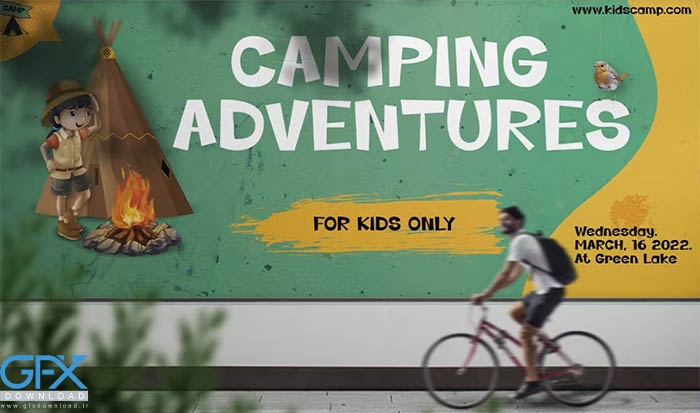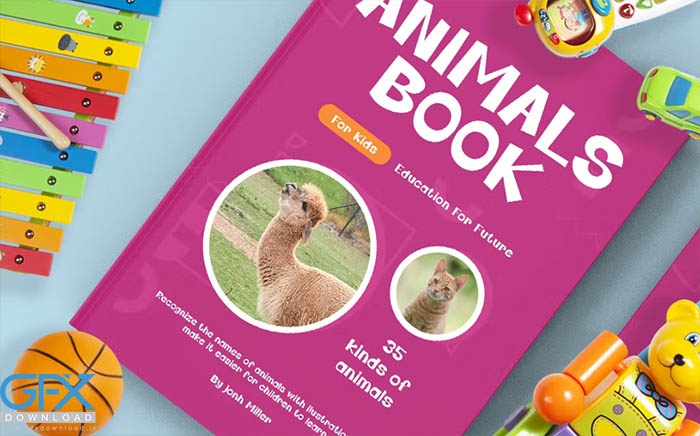
فونت سرگرمی و شادی کودکان Green Town
فونت سرگرمی کودکان Green Town
دانلود فونت انگلیسی سرگرمی و شادی کودکان Green Town
فونت عجیب و غریب با خط پایه فنری که مناسب برای سرگرمی و شادی کودکان در هر کاری است. فونت سرگرمی و شادی کودکان Green Town ایده آل برای جلد کتاب های کودکان، بازی های رومیزی، پوسترهای رویدادهای کاوش، فونت وسایل مدرسه، پوسترها، جلدهای یوتیوب، تصاویر کوچک یوتیوب، جلد صفحات رسانه های اجتماعی و غیره.
فونت انگلیسی کودکان Green Town